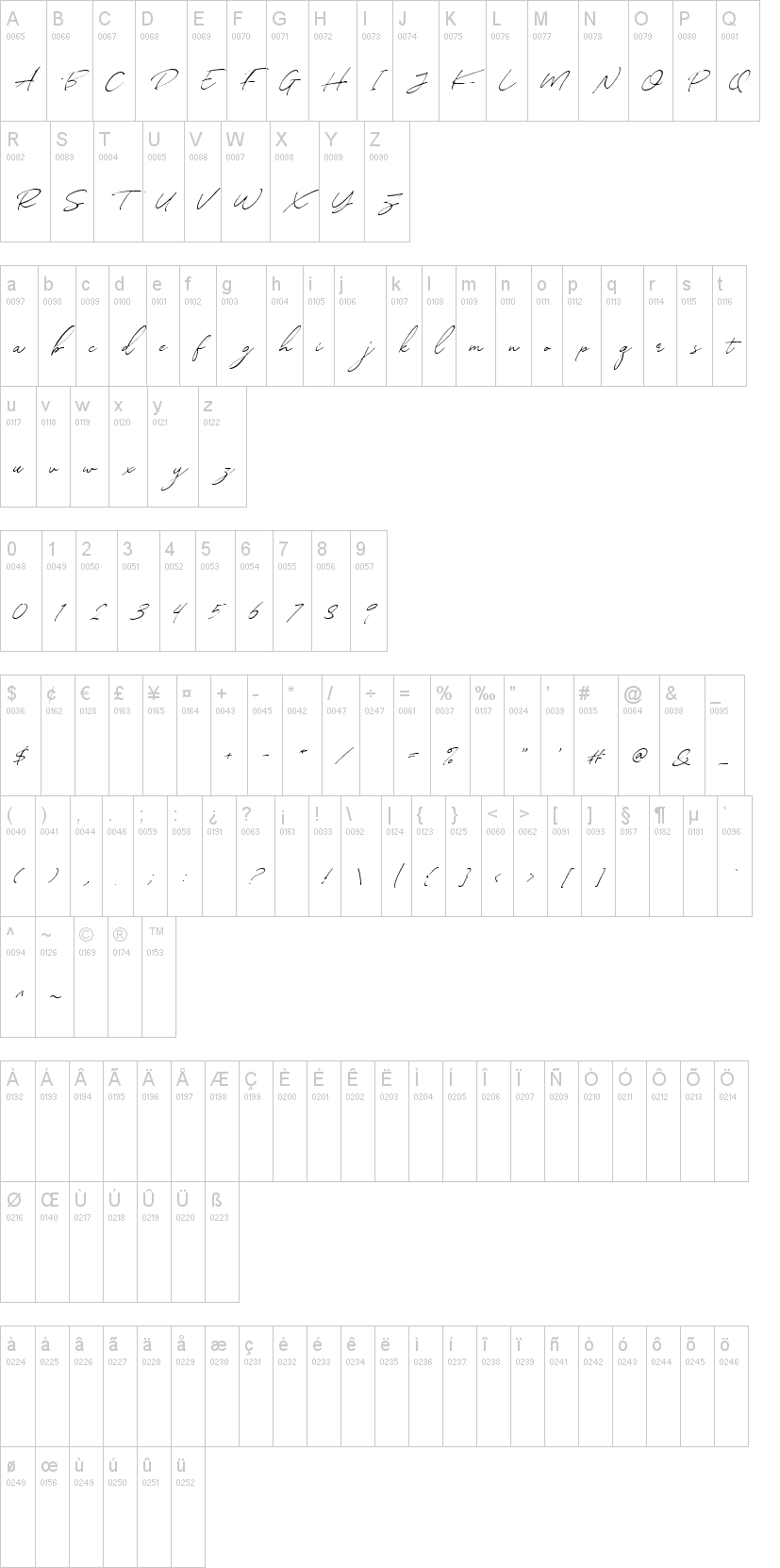
William Letter Signature是一款简洁大方的英文字体,它拥有优雅流畅的笔画,给人以清新自然的感觉。它的设计元素来源于19世纪的传统英文字体,拥有优美的曲线,非常适合用于报刊、书籍、海报等印刷品的设计。同时它也可以用于网页设计,可以带给用户清新的视觉体验。内容介绍
William Letter Signature是一款非常不错的手写艺术字体,具有很好的视觉感,适合于文化类的宣传设计、商业类品牌的广告和产品包装设计以及个性化文字排版等较多场景。